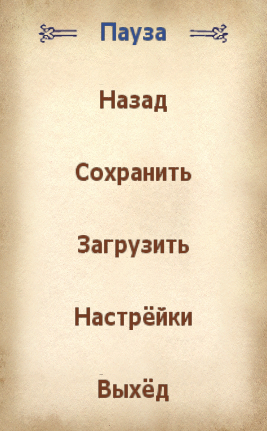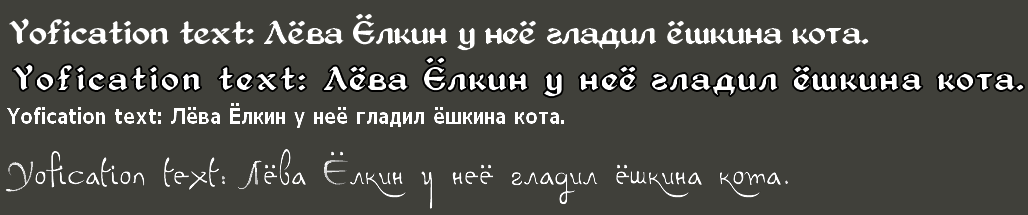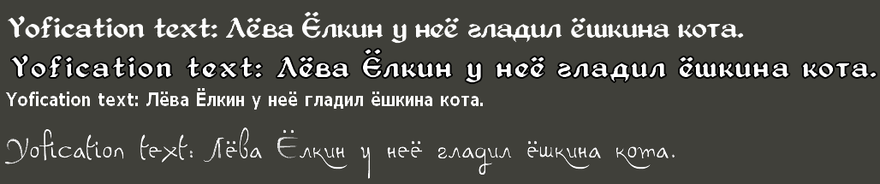
Это оригинальные шрифты, взятые из российского издания игры от компании «1С-СофтКлаб». В них поддерживаются английский и русский алфавиты. Я дополнительно модифицировал шрифты, добавив в каждый буквы Ё ё (чего не было в оригинальных шрифтах). Если вы играете с модами, где переводчики модов «по ошибке» добавляли букву Ё и она не отображалась, то с этими шрифтами, буква будет отображаться. (Печатать самому букву Ё при создании персонажа или названии предметов/зелий технически невозможно). Полезно для переведённых модов, где переводчики забыли о том, что в оригинальных шрифтах буква Ё не поддерживается.